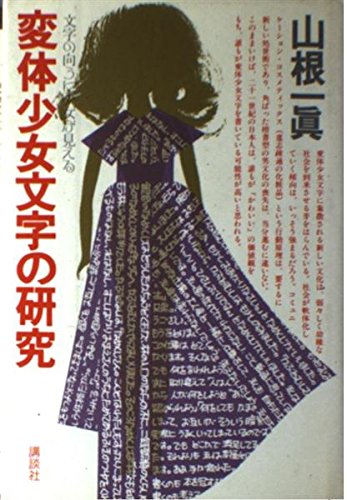
まるもじ体
女子中高生が手書きしたような「丸文字」を表現したダイナフォントの書体。明るくかわいらしい印象を与えるその字形は、主に女性や子供向けのデザインに適している。
丸文字フォント・まるもじ体の組見本(W3)
丸文字
丸文字は手書き文字の中で角を丸くした書体で、「ルンルン文字」、「まんが字(マンガ字)」、「丸字」、「ブリッ子文字」、「ネコ字」とも呼ばれている。手書き文字の書体とされ、丸ゴシック体とは異なる書体として扱われている。仮名漢字交じりの日本語の文章は、文字の特徴から角ばった箇所が目に付きやすく、文字や文章の印象が硬くなることを回避するために1970年代から1980年代に女子小中高生の間で広く用いられていた手書き文字。
丸文字体について紐解かれた「変体少女文字の研究―文字の向うに少女が見える」
丸文字体についての研究がなされた著書「変体少女文字の研究―文字の向うに少女が見える」は、ノンフィクション作家・山根一眞による著書で2年近い取材を経て1986年2月に講談社から発行された。
山根一眞による調査結果では、同書でいう変体少女文字「丸文字体」は1974年までには誕生しており、1978年に急増したとされている。また、少女らが書く丸文字の普及の一因として、70年代前半に創刊した「an・an」や「non-no」といった女性向けファッション誌で使われていた書体「ナール」(1972年発表)を挙げている。ナールとは文字の先端が丸く処理されふっくらとした字体をもつ写真植字。
また同書では、少女達が書く丸文字の流行の要因として1970年代前半に創刊した『an・an』や『non-no』といった女性向けファッション誌で使われていた、文字の先端が丸く処理されふっくらとした字体をもつ書体「ナール」(1972年発表)の存在が挙げられている。
女子中高生の中で隆盛を誇ってきた丸文字であるが、AERAの1997年6月30日号にて「女子高生に広まる、変なとんがり文字 「丸文字」の時代は終わった」というタイトルで記事が書かれ、丸文字の流行が終わりを告げて新たに、トメのしっかりしたカクカクした文字である長体ヘタウマ文字やタギング文字が広がりつつあるとされている。